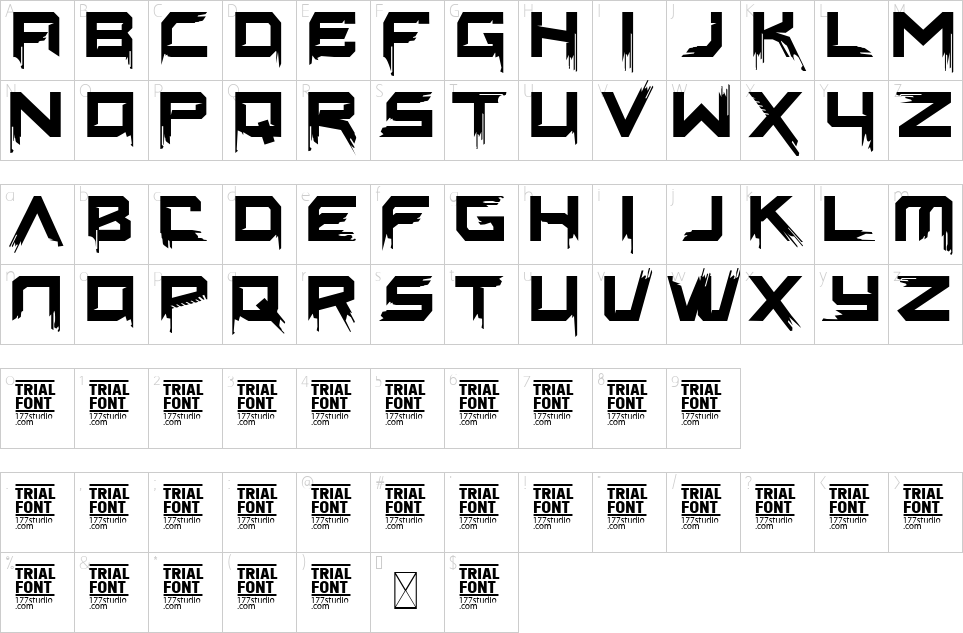
Descubra Machine Learning, uma fonte de inteligência artificial para Windows e Mac, especialmente projetada pela 177studio.com. Esta fonte foi descarregada 591 vezes, evidenciando seu grande potencial e a apreciação por designers e desenvolvedores. Ideal para aplicar um toque de sofisticação ou de uma maneira inovadora a projetos digitais, Machine Learning pode ser o recurso gráfico que lhe falta para dar um novo impulso ao seu trabalho. Descubra agora esta fonte incrível para seus projetos de design e desenvolvimento.